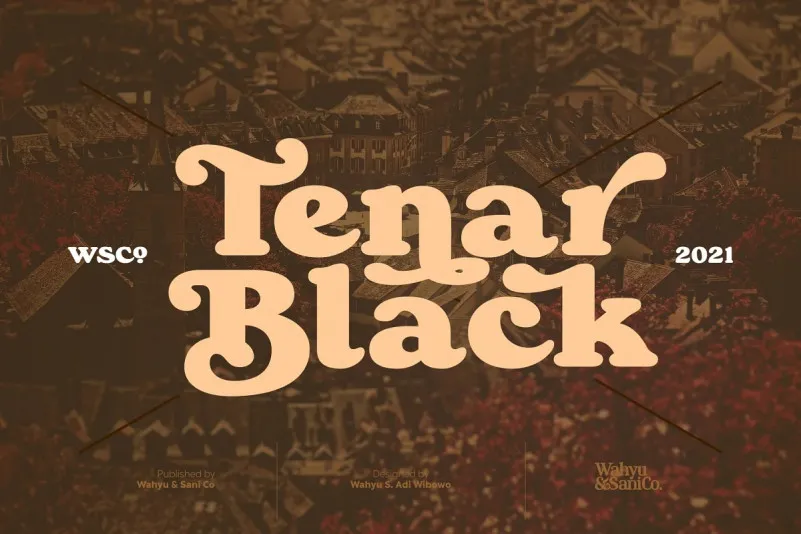
A fonte “Tenar Black Serif” é uma escolha inusitada para designers que buscam algo diferente na tipografia. Com seus traços redondos e desenhados para destaque, esta serif é perfeitamente adaptável a designs de temática clássica ou retro. Seu estilo único combina elementos vintage com um toque moderno, fazendo-a ideal para aplicar em anúncios, posters e outros ambientes onde uma forte identidade visual é essencial. A fonte conta com 362 caracteres, incluindo alternativas e ligaduras que a tornam ainda mais versátil. Seja você um designer de revistas antigos ou de posters atuais, “Tenar Black Serif” pode oferecer o charme exótico necessário para destacar seu trabalho. Sua compatibilidade com 61 línguas latino-americanas (entre outras) expande suas possibilidades criativas sem limites. Em um mundo que busca originalidade e estilo único, “Tenar Black Serif” é uma fonte de inspiração perfeita para quem procura trazer algo diferente a cada projeto gráfico.